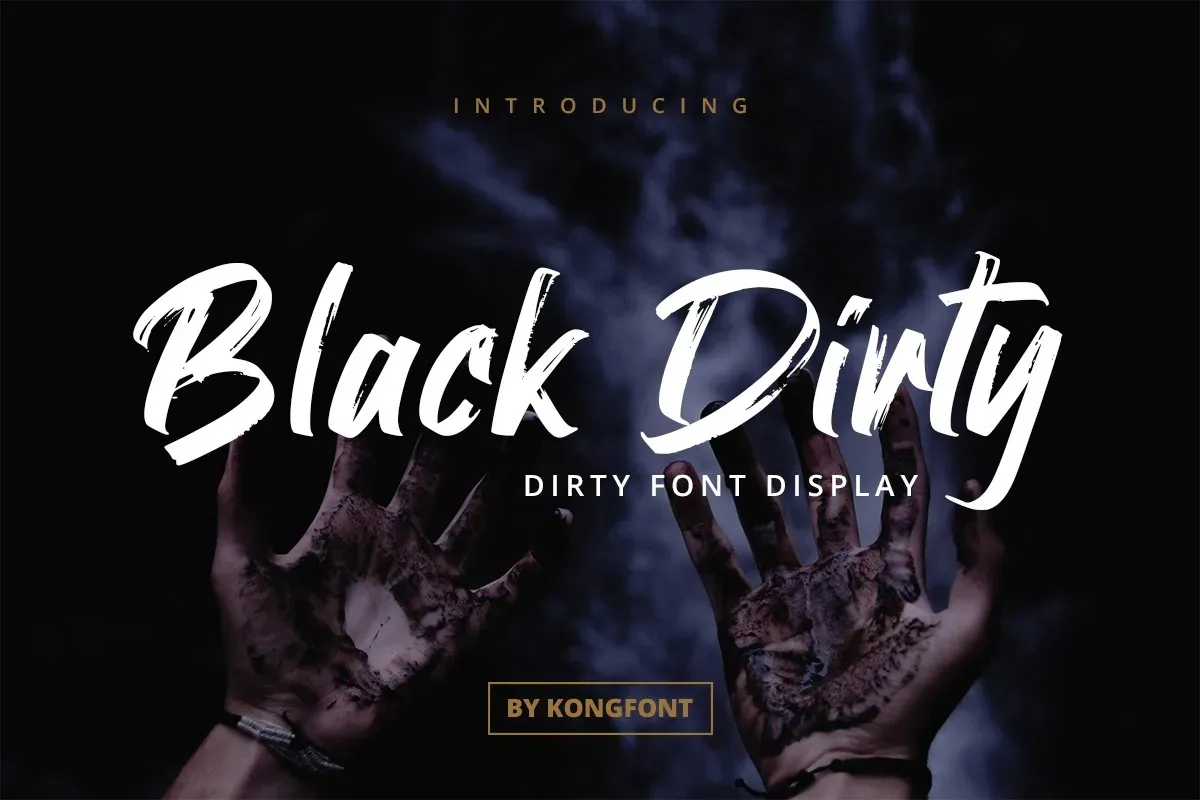
Black Dirty Font – Download Grátis
A fonte ‘Black Dirty Font’ é uma beleza de tipo produzida pela Kong Font, projetada para se adaptar a diversos usos no design gráfico, desde logotipos e convites de casamento até badais e cartazes, passando por assentos de papelaria e selos. Este script brush font oferece um aspecto natural como uma tinta escrita à mão rápida, com detalhes como swash e ligatura para tornar seu design de texto mais autêntico e fluido, remetendo à rapidez e liberdade da escrita espontânea. Perfeito tanto para designers que procuram uma linguagem natural e casual quanto aqueles buscando expressões artísticas. Não perca esta oportunidade de dar um toque autêntico e vibrante a seus projetos visuais.